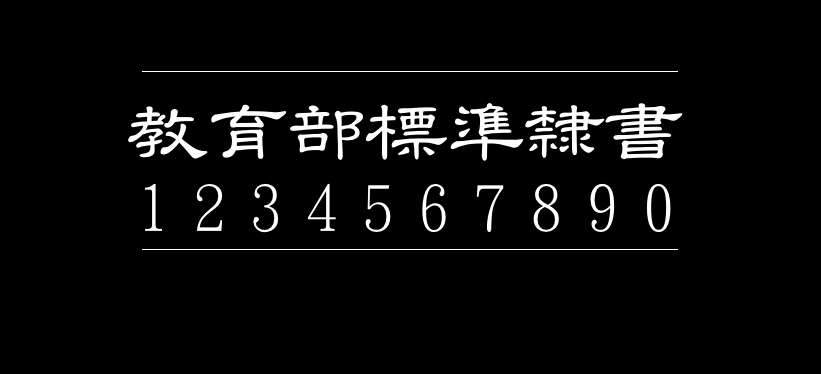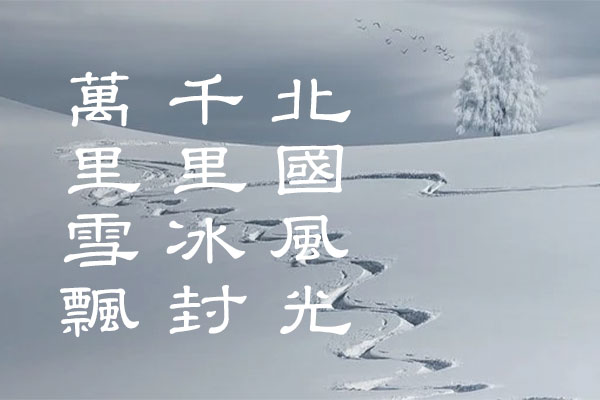
台湾教育部标准隶书
台湾教育部标准隶书(教育部隸書)来自中国台湾,依据《教育部隶书母稿》制成,目前收录中文字数为4,808 字,是依照国字标准字形写法。国字标准字体是中国台湾教育部颁布的常用标准字体表与次常用标准字体表内规定的标准字形写法。日后又经过多次修改,用于台湾出版的中小学课本、公文上,是台湾中文的规范依据。
该字体对由于是台湾地区推出的,对繁体中文支持得较好,而简体有缺字现象。